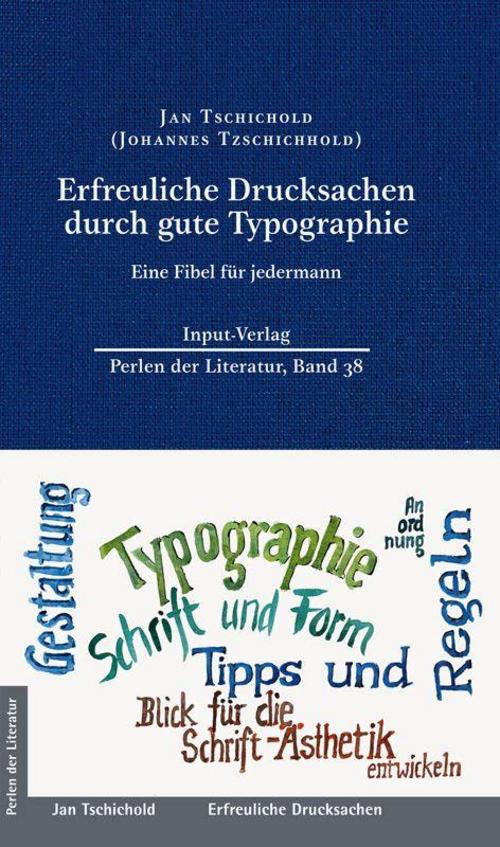
Als Dozent, Referent und Berufsschullehrer hat Ralf Plenz dieses 1960 erschienene Fachbuch hunderte Male seinen Studenten und Auszubildenden in die Hand gegeben und Begeisterung erzeugen können. Tschichold vertritt als Typograph klare Regeln und zeigt an vielen Beispielen, was gute Gestaltung gegenüber 'wilder Typographie' kann und darf. Seine Analysen sind immer überzeugend, auch wenn sie aus den Zeiten von Bleisatz und Fotosatz stammen. Jeder, der mit Text- oder Grafikprogrammen am Mac, PC oder Smartphone etwas gestaltet, kann sich mit Erfolg auf seine Hinweise und Empfehlungen berufen.